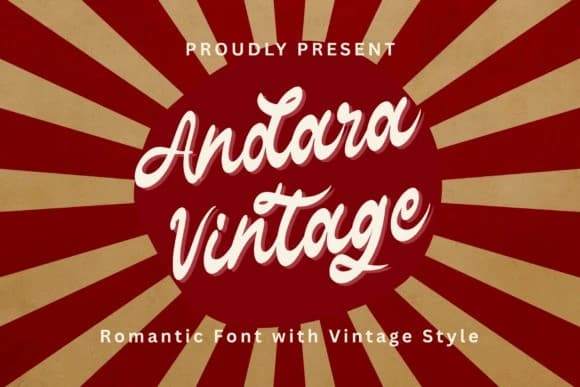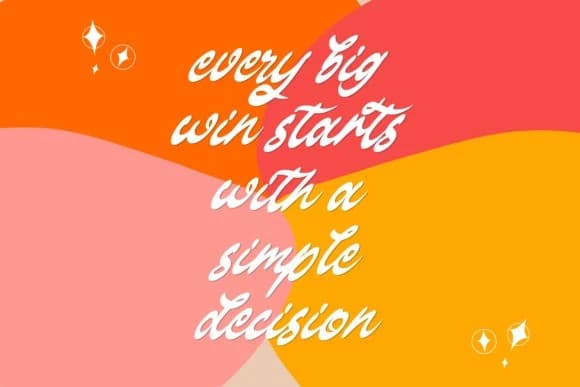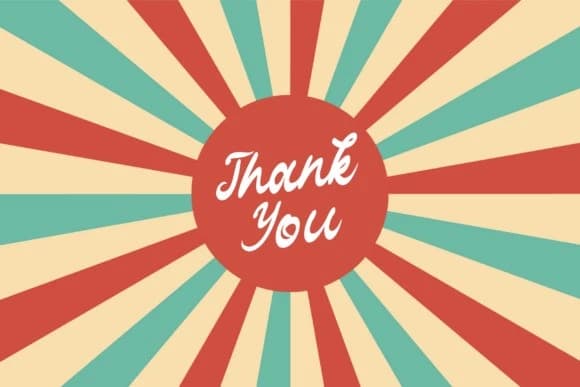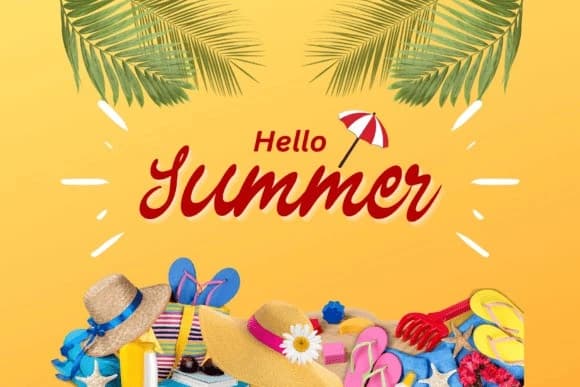
Andara Vintage Font
Andara Vintage Font, zarif bir script fontudur ve güzel bir retro ile romantik bir his verir. Pürüzsüz el yazısı çizgileri, zarif eğriler ve büyüleyici ligatürleriyle sıcak bir vintage görünüm yaratır.
Andara Vintage Font, güzel retro ve romantik bir his veren şık bir el yazısı fontudur. Pürüzsüz el yazısı çizgileri, zarif kıvrımlar ve büyüleyici ligatürler içerir; bu öğeler sıcak bir vintage görünüm yaratır.